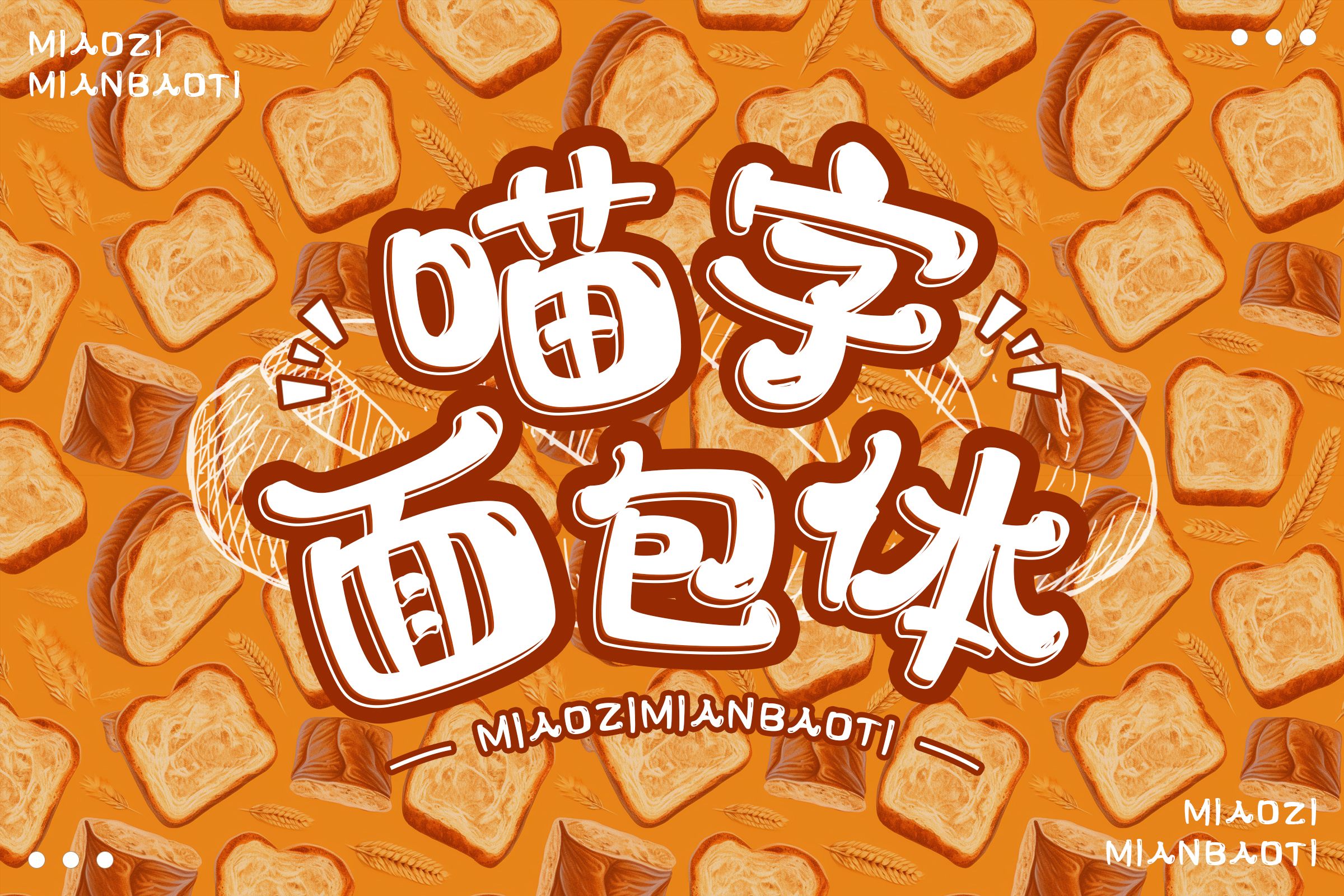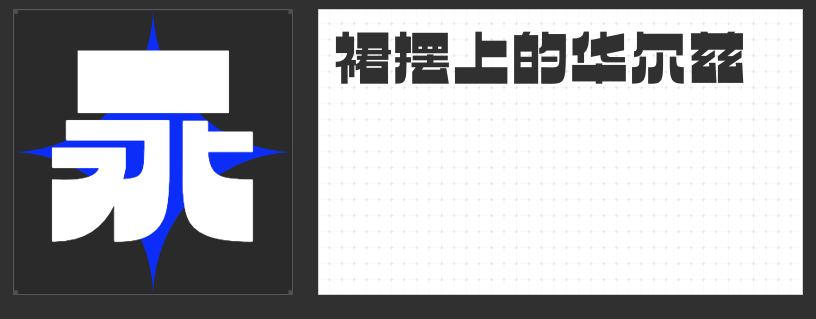
漫威英雄风采再现:动画电影封面字体精选与推荐
在漫威的浩瀚宇宙中,每一位超级英雄都拥有自己独特的个性和传奇故事。当这些故事跃然于动画电影封面时,选择合适的字体不仅能准确传达英雄的气质,还能瞬间吸引观众的眼球。以下是几款特别适合用于漫威超级英雄动画电影封面的字体推荐。
对于如雷神托尔、钢铁侠等力量型英雄,一款粗犷、棱角分明的无衬线字体再合适不过。励字暴风简 超级黑线条简洁、气势磅礴,能够完美展现英雄们的力量感和决心,让观众一眼就能感受到角色背后的强大能量。
美国队长作为漫威宇宙中的经典英雄,其封面设计常常采用复古风格的字体。高手兵克侠客体优雅而庄重,带有浓厚的时代感,能够完美契合美国队长作为二战时期超级士兵的身份背景,同时传递出英雄不屈不挠、坚守信念的精神内核。
对于像银河护卫队、奇异博士等充满科幻元素的英雄,一款具有未来感和科幻感的定制字体无疑是最佳选择。励字逆反差圆舞简 超级黑线条流畅而富有变化,能够营造出一种超越现实的神秘氛围,让观众对电影内容充满好奇和期待。
4. 喵字面包体
虽然漫威宇宙以成人向的超级英雄为主打,但偶尔也会出现如蜘蛛侠(尤其是早期设定中的)这样活泼可爱的角色。对于这类英雄的动画电影封面,一款圆润、可爱的卡通字体能够很好地展现角色的性格特点,吸引年轻观众的目光。
综上所述,选择合适的字体对于漫威超级英雄动画电影封面来说至关重要。它不仅能够提升封面的视觉效果,还能准确传达英雄的气质和故事主题,为观众带来更加沉浸式的观影体验。